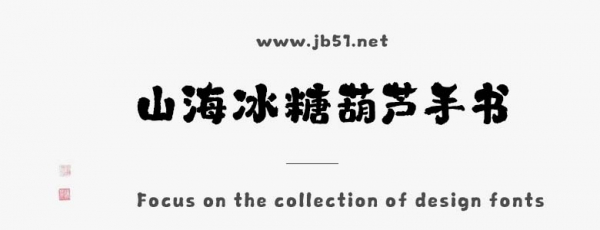
山海冰糖葫蘆手書(shū)W是由山海字庫(kù)出品的字體,這款字體筆觸適中,具有很好的視覺(jué)感,適合應(yīng)用于藝術(shù)設(shè)計(jì)、平面宣傳設(shè)計(jì)、網(wǎng)頁(yè)設(shè)計(jì),書(shū)法字帖等領(lǐng)域,需要的朋友可以前來(lái)本站下載。